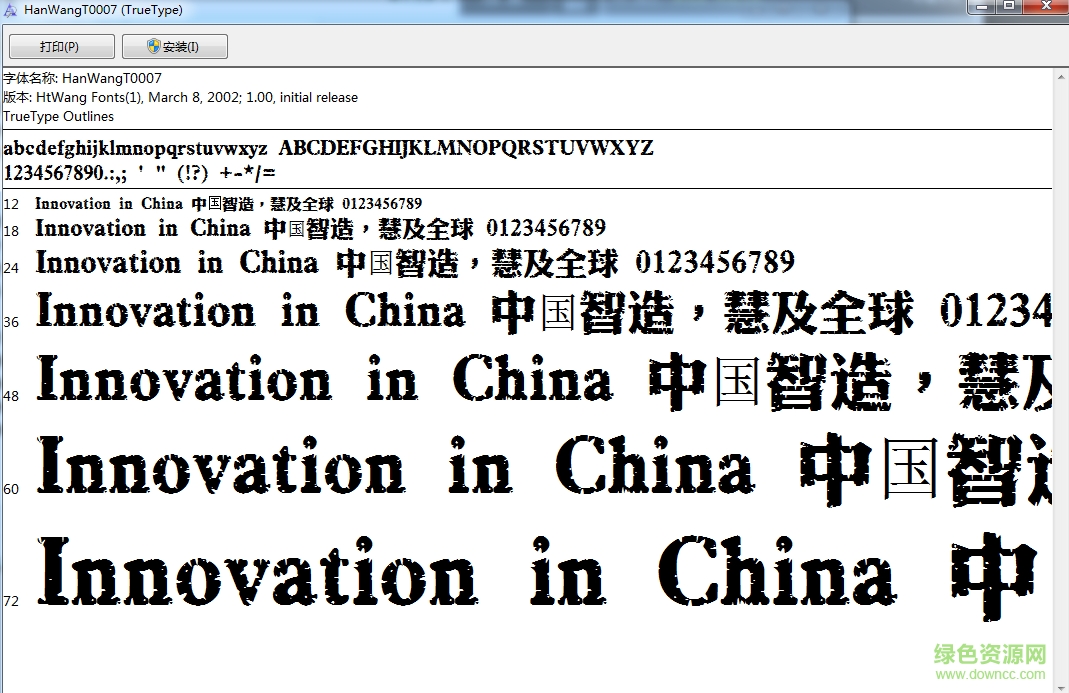
王漢宗拓仿黑體簡(jiǎn)
王漢宗拓仿黑體是是一款拓印刷法字體,精簡(jiǎn)清新的設(shè)計(jì)讓人很有好感,適合于廣告設(shè)計(jì)、印刷排版、編輯打印等行業(yè)需要,綠色資源網(wǎng)誠(chéng)意推薦!
字體簡(jiǎn)介
王漢宗拓仿黑體作為i酷安很有特色的王漢宗字體,深受設(shè)計(jì)師們的喜愛(ài),古典中國(guó)風(fēng)的墨跡讓你的書(shū)法設(shè)計(jì)更加出色!
王漢宗拓仿黑體簡(jiǎn)體